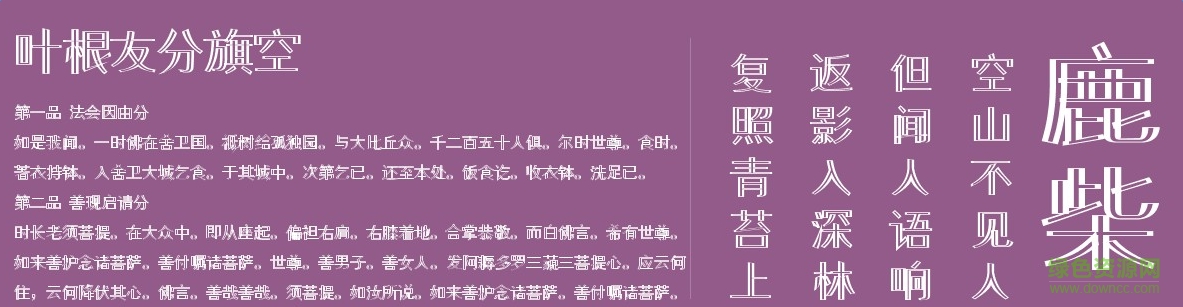
葉根友分旗空
葉根友分旗空字體是一款由知名書法家葉根友創(chuàng)造的字體,比劃圓潤,適用于廣告、藝術(shù)設(shè)計(jì),海報(bào)設(shè)計(jì)等方面,有需要的朋友們不要錯(cuò)過了。歡迎大家來綠色資源網(wǎng)踴躍下載哦!
葉根友分旗空是一款2016年5月新發(fā)布的一款字體,似空而不空的風(fēng)格,以線條組成的中國漢字,對現(xiàn)在黑體看多了的電腦用戶來說是一種新鮮的感覺,我們可以用更新的思維來探索中國漢字字體的發(fā)展,而不局限橫豎撇捺的方正平劃,葉根友分旗空適用于各類海報(bào)標(biāo)題,個(gè)性廣告書法漢字等載體上,具體怎么用還是看各位看官心中美感了。
葉根友分旗空字體,用途廣泛,是葉根友先生的手寫字體,非常有特色,似空不空,適合場合很多,各位字體收藏者可以來看看。